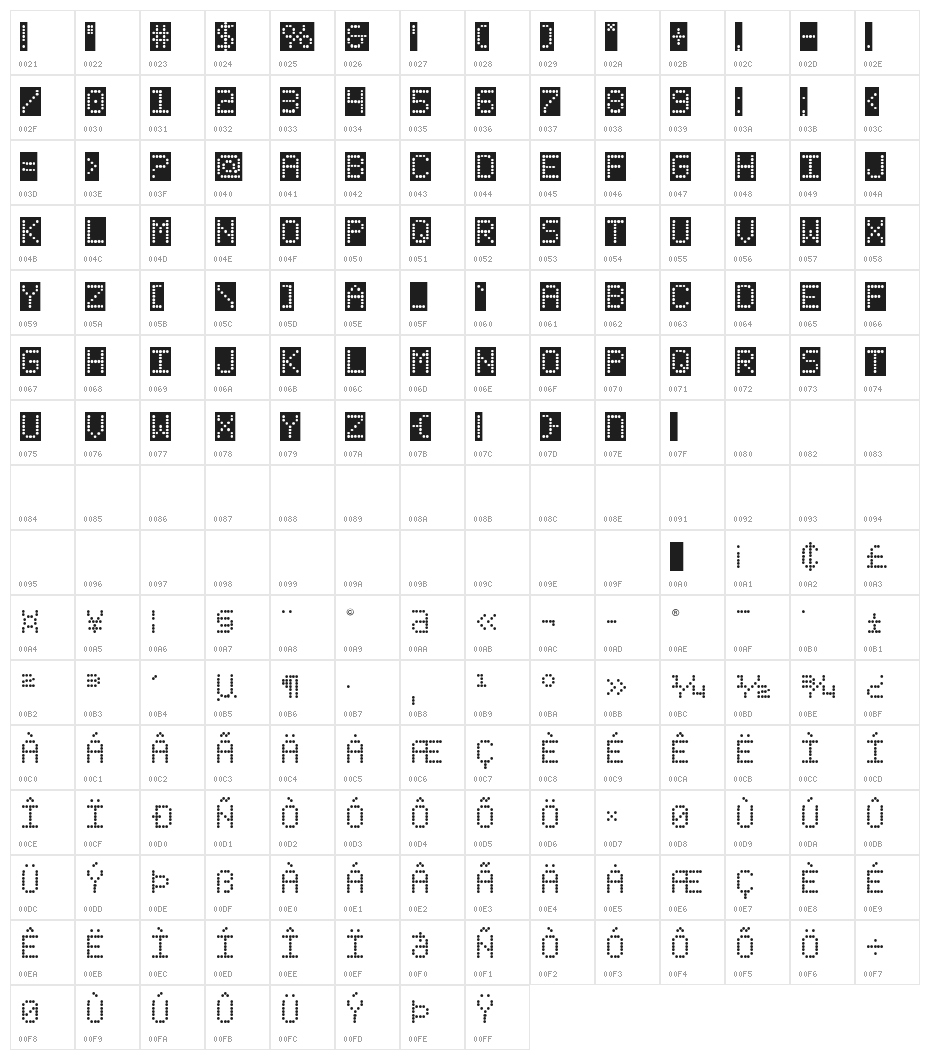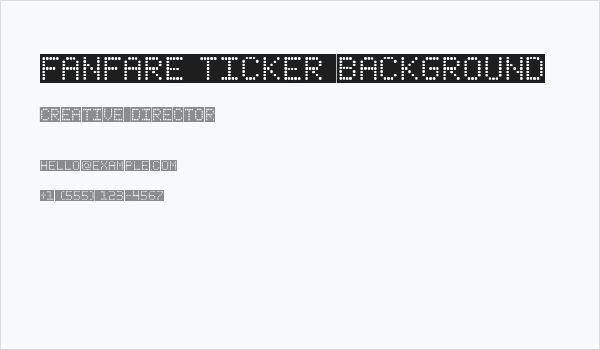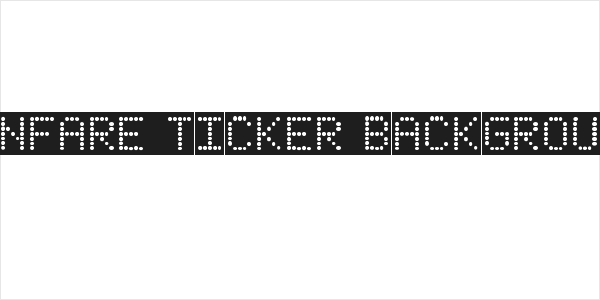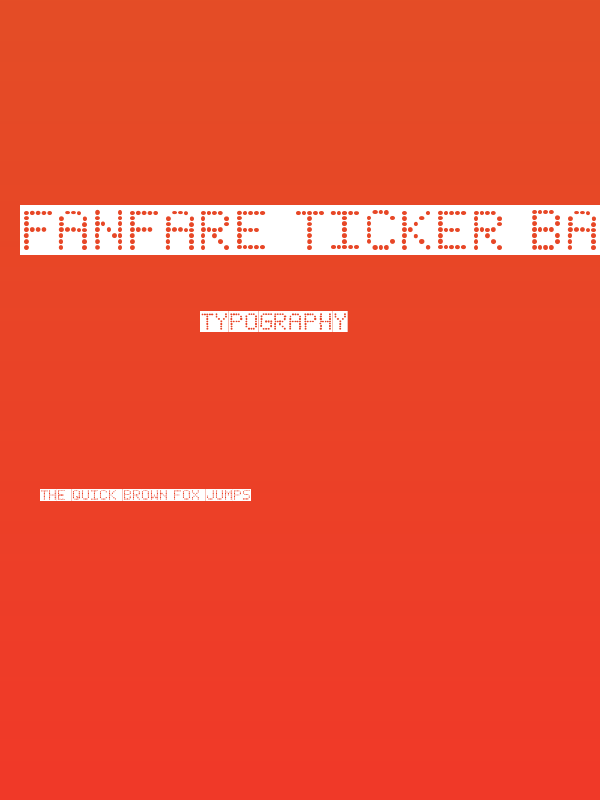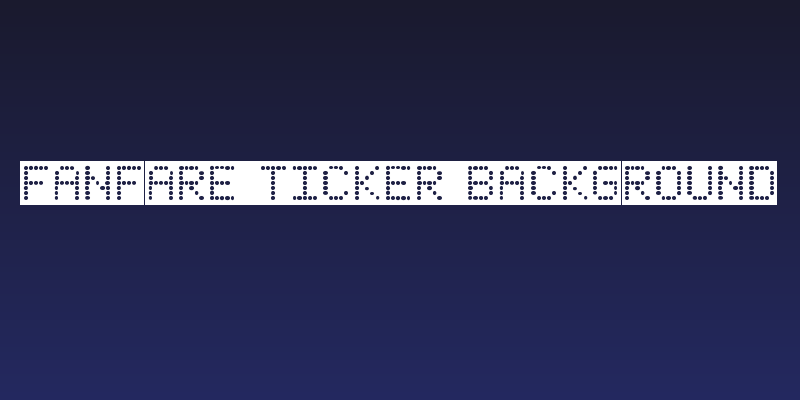
Fanfare Ticker Background Font
| Gesamtstil | Retro, Digital |
| Anwendungsfall | Headlines, Logos, Digital Displays |
| Vorgeschlagene Projekte | Perfect for digital-themed designs, retro video game graphics, tech event posters, or any project needing a nostalgic electronic feel. |